Vier Grundstriche in einem Wort, alle exakt gleich breit. Nach fünf Wochen regelmäßigem Brush-Lettering-Training war mir das noch nicht gelungen. Ich hatte "Frühling" auf ein frisches Blatt geschrieben, eigentlich nur um einen Farbverlauf von Dunkelblau zu Hellblau zu testen, und erst beim zweiten Hinsehen fiel mir auf, dass keiner der vier Abstriche breiter geraten war als die anderen. Genau dieses Blending – der weiche Übergang zwischen zwei Farbtönen mit dem Brush Pen – hatte mich bis dahin mehr genervt als jede andere Technik aus meinem Handlettering-Kurs.
Warum mein erster Verlauf aussah wie ein Wasserschaden
Mein erster Fehler war banal. Ich hatte stinknormales Druckerpapier eingespannt, weil ich dachte, Papier sei Papier, so wie eine Datei in Illustrator ja auch erstmal nur eine Datei ist. Die Spitze hakte bei jedem Abstrich, zog kleine Fasern mit sich, und aus dem geplanten sanften Übergang wurde ein grauer Fleck, der eher nach verschüttetem Kaffee aussah als nach Lettering. Wie genau sich Papiersorte und Stiftspitze gegenseitig beeinflussen, ist eigentlich ein eigenes großes Thema, das ich an anderer Stelle ausführlicher durchgehe. Hier reicht die Kurzfassung: Ohne eine Oberfläche, die der Tinte kurz Zeit lässt, sich zu vermischen, bevor sie einzieht, bleibt jeder Blending-Versuch Glückssache. Dazu kommt, dass eine bereits ausgefranste Spitze das Problem verschärft, aber wie genau sich Brush-Pen-Spitzen mit der Zeit abnutzen, ist wieder ein anderes Thema für sich.
Im Handlettering Kurs wird genau das früh angesprochen: Material ist die halbe Miete. Für Blending mit wasserbasierten Stiften braucht es Papier mit einer gewissen Dichte, sonst hat die Tinte keine Chance, überhaupt zu verlaufen, bevor sie im Fasergewebe verschwindet. Das gilt für alle 26 Buchstaben des lateinischen Alphabets gleichermaßen, nicht nur für die, die man gerade übt.
Druckkontrolle entscheidet zwischen Verlauf und Kleckerei
Sobald das Papier stimmte, war Druckkontrolle die nächste Hürde. Blending scheitert fast immer daran, dass der Abstrich ungleichmäßig bleibt: mal zu viel Druck, mal zu wenig, und schon entstehen kleine Tintenseen an Stellen, wo eigentlich ein weicher Übergang hin sollte. Wie eine gleichmäßige Druckkurve über eine ganze Zeile hinweg aussieht, zeige ich an anderer Stelle im Detail. Für das Blending reicht die Beobachtung, dass die Spitze bei starkem Druck breiter aufliegt und bei leichtem Druck fast wie ein Fineliner schreibt, und dass genau dieser Übergang den Farbverlauf entweder rettet oder ruiniert. Auch die Anatomie der Buchstaben, also wo Ober- und Unterlängen ansetzen, spielt beim Blending mit hinein, ist aber ein eigenes Kapitel, das ich hier nicht aufmache.
Als Linkshänderin gegen die eigene Handkante
Als Linkshänderin stehe ich beim Blending vor einer Herausforderung, die viele Standard-Anleitungen schlicht ignorieren. Während Rechtshänder ihre Hand von der frisch geschriebenen, nassen Tinte wegbewegen, schiebt sich meine Handkante praktisch direkt darüber. Will ich einen sanften Verlauf von Dunkelblau zu Hellblau anlegen, verwische ich das Ergebnis oft im selben Moment mit dem eigenen Handballen.
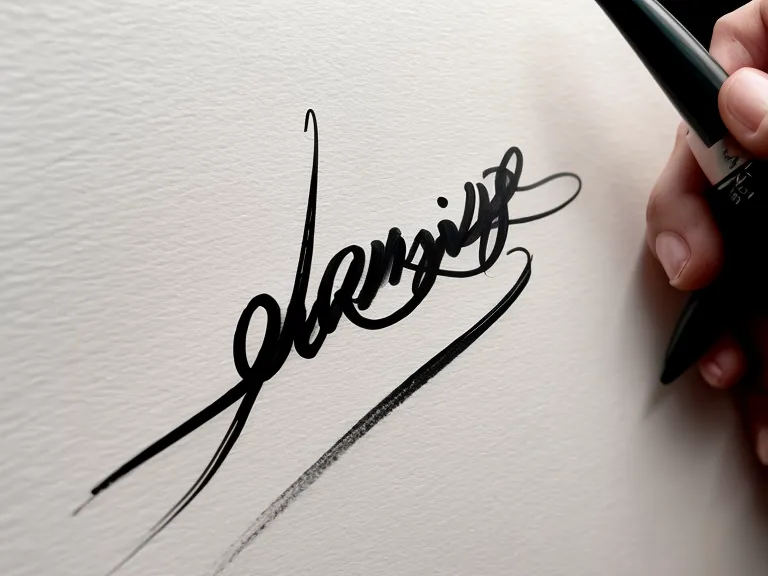
Gelernt habe ich, das Papier extrem schräg zu legen und den Stiftwinkel anders anzusetzen als in den meisten Erklärvideos gezeigt. Der Handlettering Kurs erklärt die allgemeine Technik gut, doch die Anpassung an meine eigene Handhaltung musste ich mir selbst erarbeiten. Inzwischen arbeite ich oft von rechts nach links oder lege ein zweites Blatt Papier als Schutz unter die Hand. Wer sich generell für andere Schriftstile interessiert, findet in diesem Vergleich für verschiedene Schriftstile weitere Ansätze, wie sich die Handhaltung je nach Stil anpassen lässt. Den Stift kann ich nicht wie ein Rechtshänder ziehen, ich muss ihn eher über das Papier schieben, ohne die empfindliche Spitze zu ruinieren. Das war für mich der eigentliche Umweg, nicht die Farbtheorie.
Von Dunkel nach Hell: Blending-Technik mit der Palette
Es gibt zwei Wege zu blenden: Stift-auf-Stift oder die Palette-Technik. Bei Letzterer gibt man die dunkle Farbe auf eine glatte Plastikoberfläche – eine Klarsichtfolie reicht auch – und nimmt die Pigmente mit der helleren Spitze eines zweiten Stifts auf. Twin-Tip-Stifte mit zwei verschiedenen Spitzen eignen sich dafür besonders gut, weil eine Seite fürs Auftragen und eine fürs Abnehmen der Farbe reserviert bleiben kann. Wer gerade keinen Brush Pen zur Hand hat, kann ähnliche Verläufe auch über Faux Calligraphy annähern, allerdings mit ganz anderen Mitteln und einem eigenen Lernpfad.
Der erste saubere Übergang von einem tiefen Navy zu einem hellen Himmelblau gelang mir, ohne dass die helle Spitze dauerhaft dunkel blieb, und das fühlte sich nach echtem Fortschritt an. Die Regel "von Dunkel nach Hell" ist dabei zentral: Wer mit einem dunklen Stift direkt in eine helle Fläche malt, riskiert, dass der helle Stift die dunkle Farbe aufsaugt und danach nie wieder sauber schreibt. Federnder Widerstand in den Fasern der Spitze, sobald der erste Druck ansetzt, fühlt sich bei jedem Stift ein bisschen anders an, bei einem guten Brush Pen spürt man das im Finger, bevor man es überhaupt auf dem Papier sieht.
Wer lieber digital arbeitet, hat es an dieser Stelle leichter. Für alle, die keine Lust auf tintenverschmierte Finger und eine ramponierte Tischdecke haben, lohnt sich ein Blick auf den Digital Lettering Kurs fürs iPad. Dort ist Blending eine Frage von Ebenen und Deckkraft, was insgesamt weniger Frustpotential mit sich bringt, wenn man wie ich dazu neigt, frische Tinte mit dem Ärmel zu verschmieren.